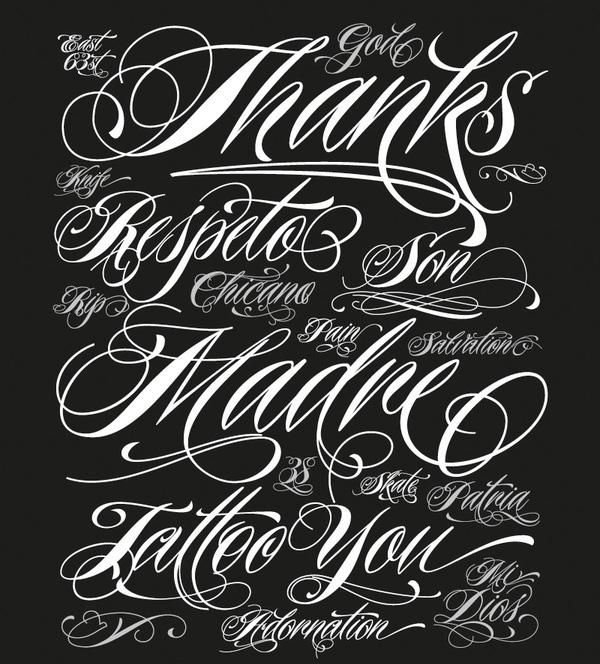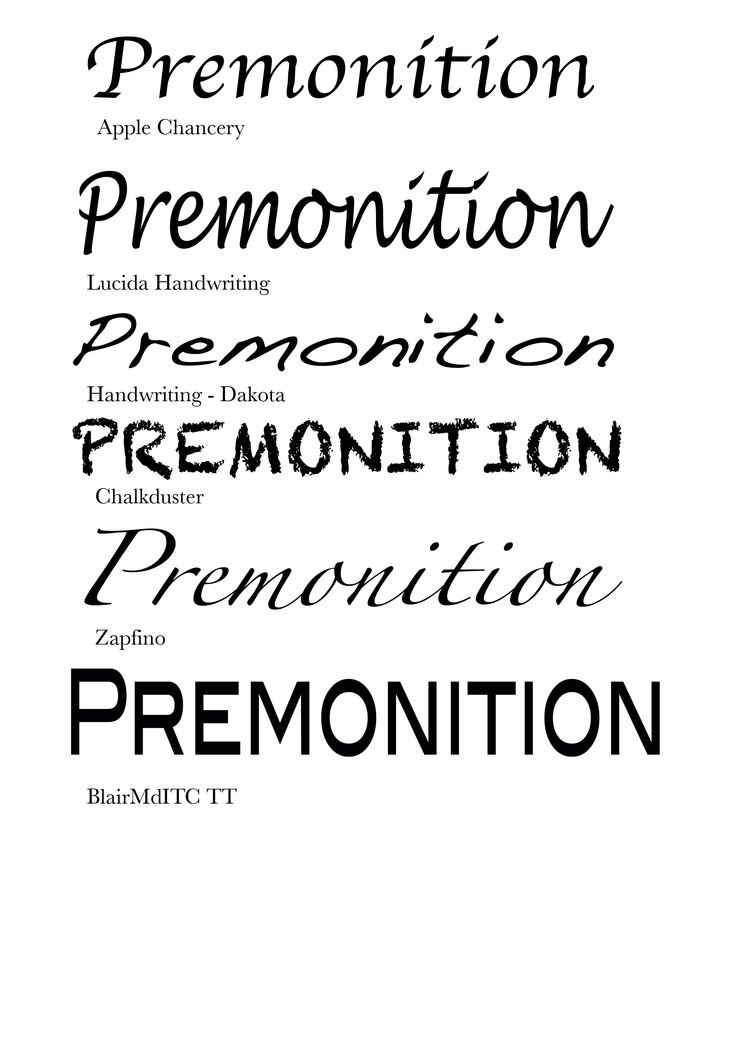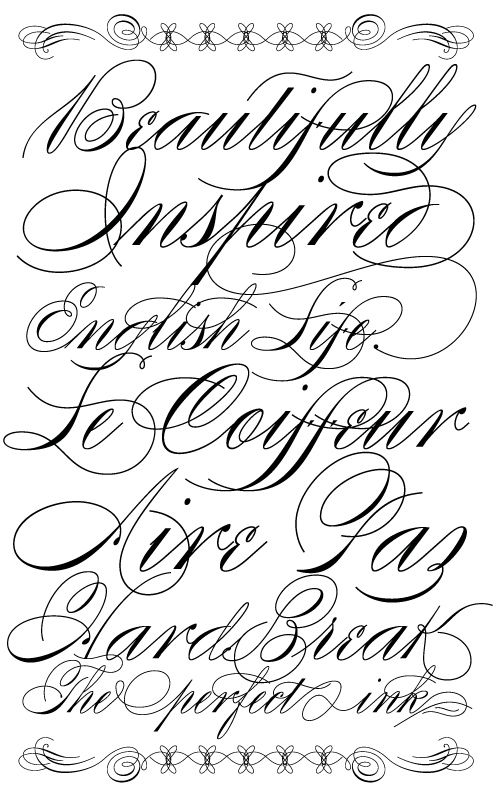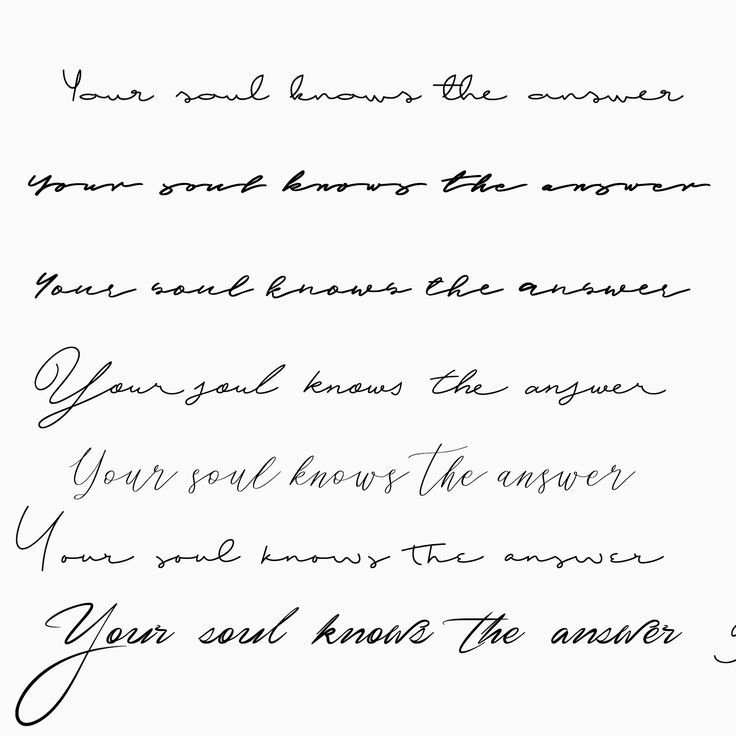
Красивый шрифт для тату: рекомендации и стильные идеи
Сейчас очень многие начинаю делать тату, которые по их мнению выделяют их из толпы, при этом совсем недавно такая популярность отмечалась у мужчин, сейчас же этим украшают себя и девушки. Но некоторые боятся украшать свое тело разнообразными рисунками, не только потому, что это на всю жизнь, но и несет некоторое секретное значение, которое может изменить жизнь обладателя в совсем другую сторону. Поэтому все чаще делают надписи на разных участках тела – тут каждый вкладывает в надпись свой характер и стиль жизни. Немаловажно – выбрать красивый шрифт для тату, разнообразие которых просто невообразимо на данный момент времени.
Выбор шрифта для будущего тату
Если было решено сделать тату в виде надписи, необходимо в первую очередь разобраться во всех аспектах такого типа рисунков на теле. На сегодняшний день можно найти разнообразные вариации стилей, поэтому каждый может найти для себя неповторимое и уникальное решение.
Нанесение фразы, афоризма, а также других надписей также имеет варианты, можно пофантазировать и покреативить.
Именно от шрифта будет зависить результат. Можно выбрать надпись, которая будет состоять только из одной или двух букв, также существует множество идей с длинными словосочетаниями или предложениями с глубоким философским смыслом для каждого.
Популярные направления, стили и виды шрифта, используемого для тату
Так как обилие разнообразных вариантов слишком большое, будет трудно определиться не только с выбором самой надписи, но и шрифта, ведь они все по-своему красивы. Девушкам лучше подбирать более женственные, элегантные шрифты, которые будут отличаться завитками и изгибами. Для мужчин же рекомендуются более строгие линии.
Каждый должен попытаться найти для себя оптимальный стиль, благодаря которому будет подчеркнута индивидуальность. Самые востребованные на данный моменты шрифты тату следующие:
- Каллиграфия. Данный вид шрифта может предполагаться в огромной количестве направлений, они могут отличаться уникальный почерком, а также стилем самого тату-мастера.
Чаще всего используется женщинами.
- Готика. Подход такого типа часто выбирают мужчины. Среди вариантов можно выделить те, которые хорошо читаются, а также те, форму которых сложно воспринять с первого взгляда. Логотипы рок-групп производятся именно в готическом стиле.
- Граффити. Главная особенность такого стиля – комбинирование шрифта, а также иллюстрация в одном флаконе. На данный момент можно все чаще замечать уличное искусство на теле людей.
- Национальная специфика. Тут все просто, многие страны отличаются своим шрифтом. К примеру, страны Азии, арабские и славянские страны отличаются своими особенностями письма, нюансами стилистики. Очень часто используются иероглифы Японии, но тут мастера могут и схитрить, написав совсем не то, что нужно, поэтому важно самому выбрать и при необходимости перевести фразу.
- Печатная машинка. Также можно отметить популярность надписей, которые имеют эффект написания при помощи старой машинки для печати с некоторыми недостатками.
В таком случае буквы надпись отличаются визуальными дефектами. Благодаря такому подходу, можно создать уникальный вариант надписи.
Если разобраться с основными популярными направлениями, можно намного легче выбрать надпись, но можно придерживаться и собственного видения идеального шрифта для тату.
Если же уже точно решено сделать тату, то нужно убедиться является ли мастер квалифицированным и ответственным. Он обязан использовать только стерильные перчатки и иглы.
Перед началом процедуры специалист должен дать консультацию о появлении возможных последствий, а также о том, о правильном уходе за татуировкой, а также – может потребовать медицинское свидетельство от клиента о том, что он здоров на момент нанесения тату и не страдает аллергией.